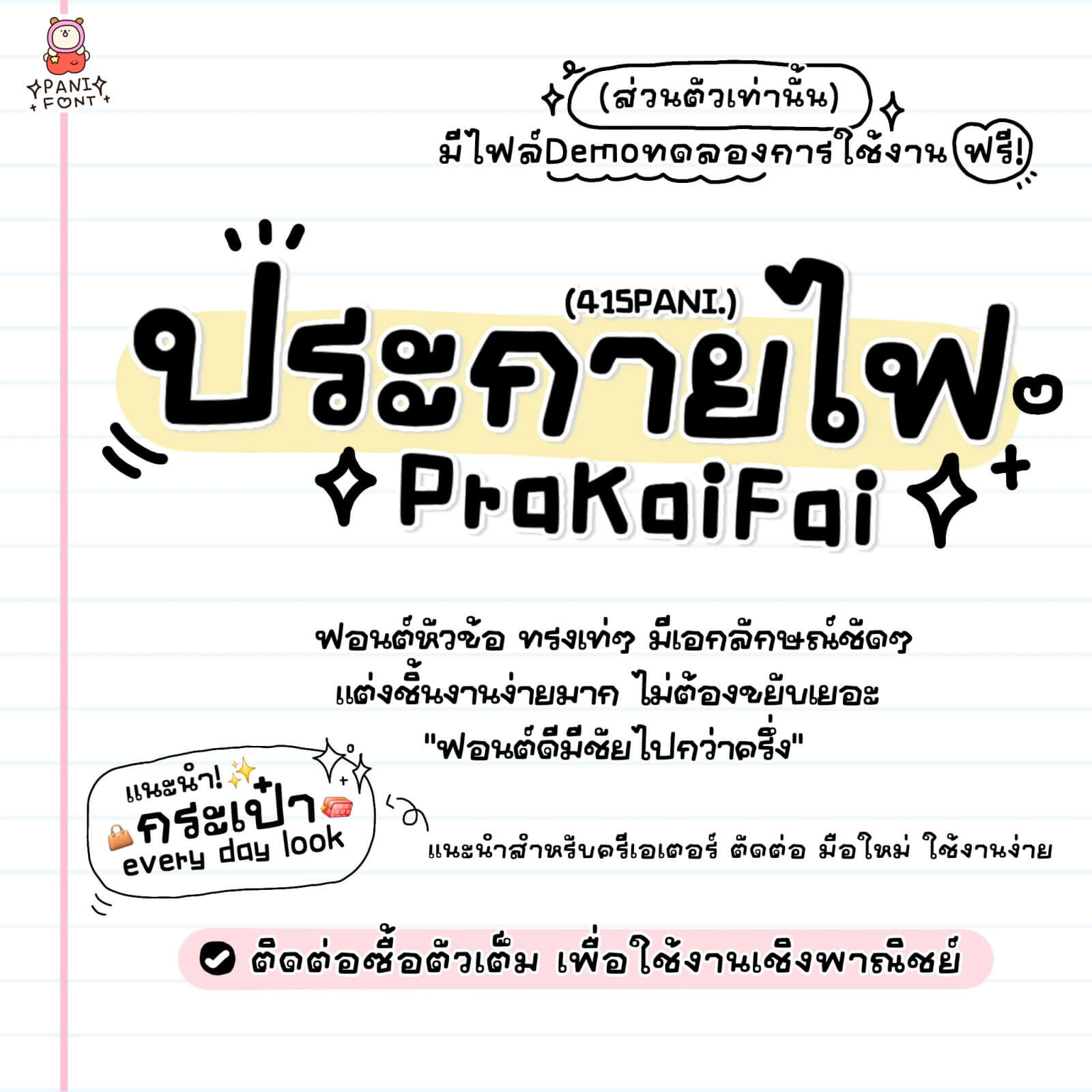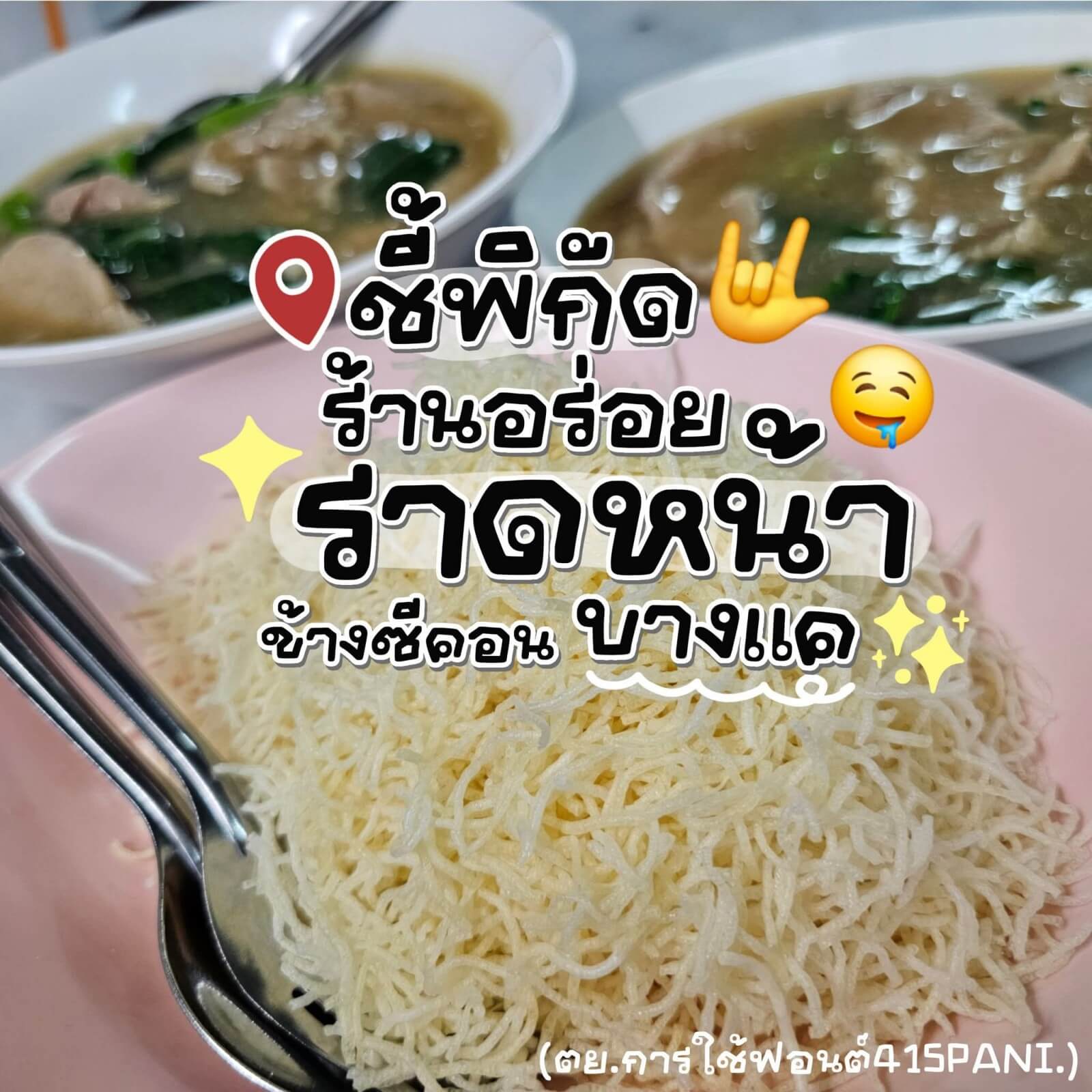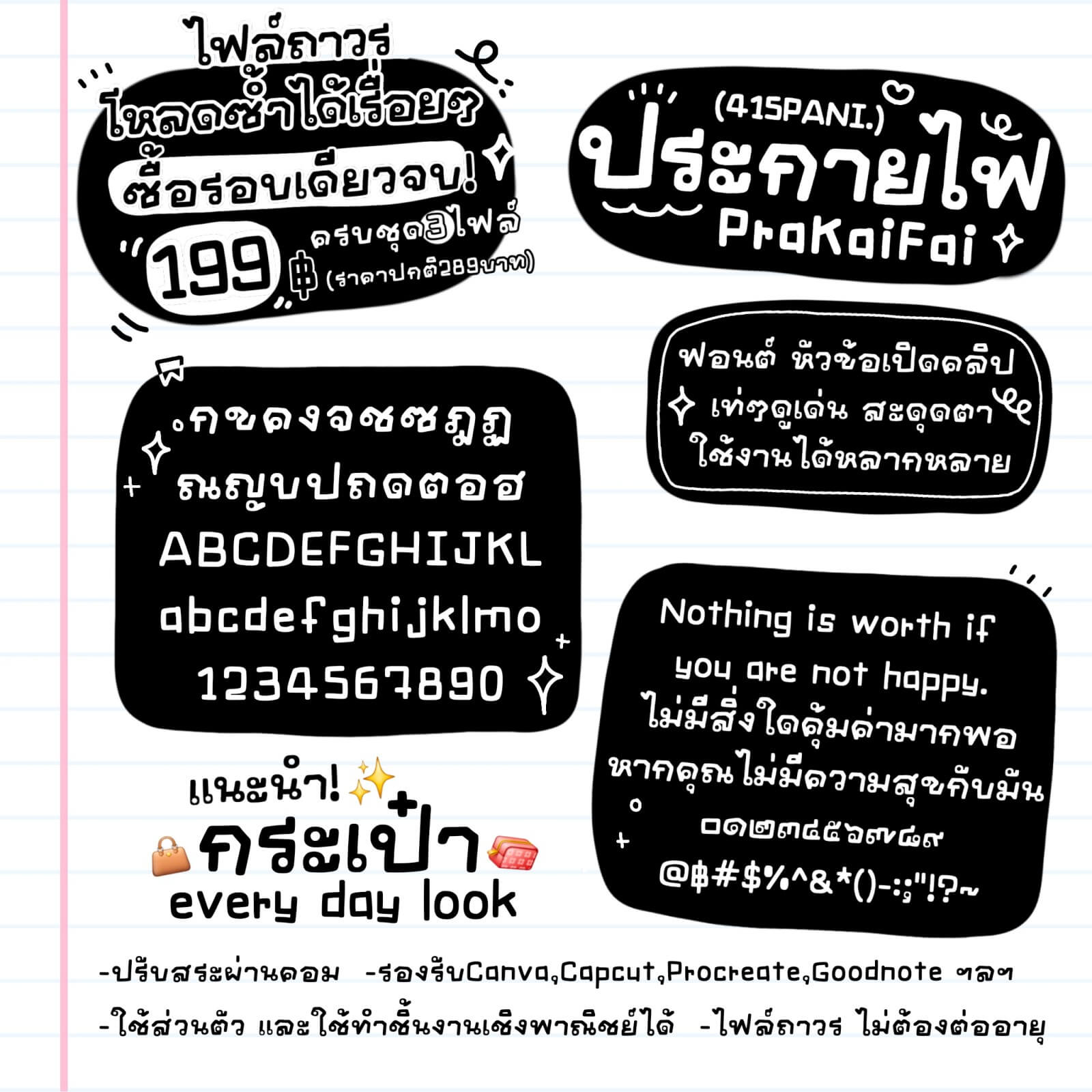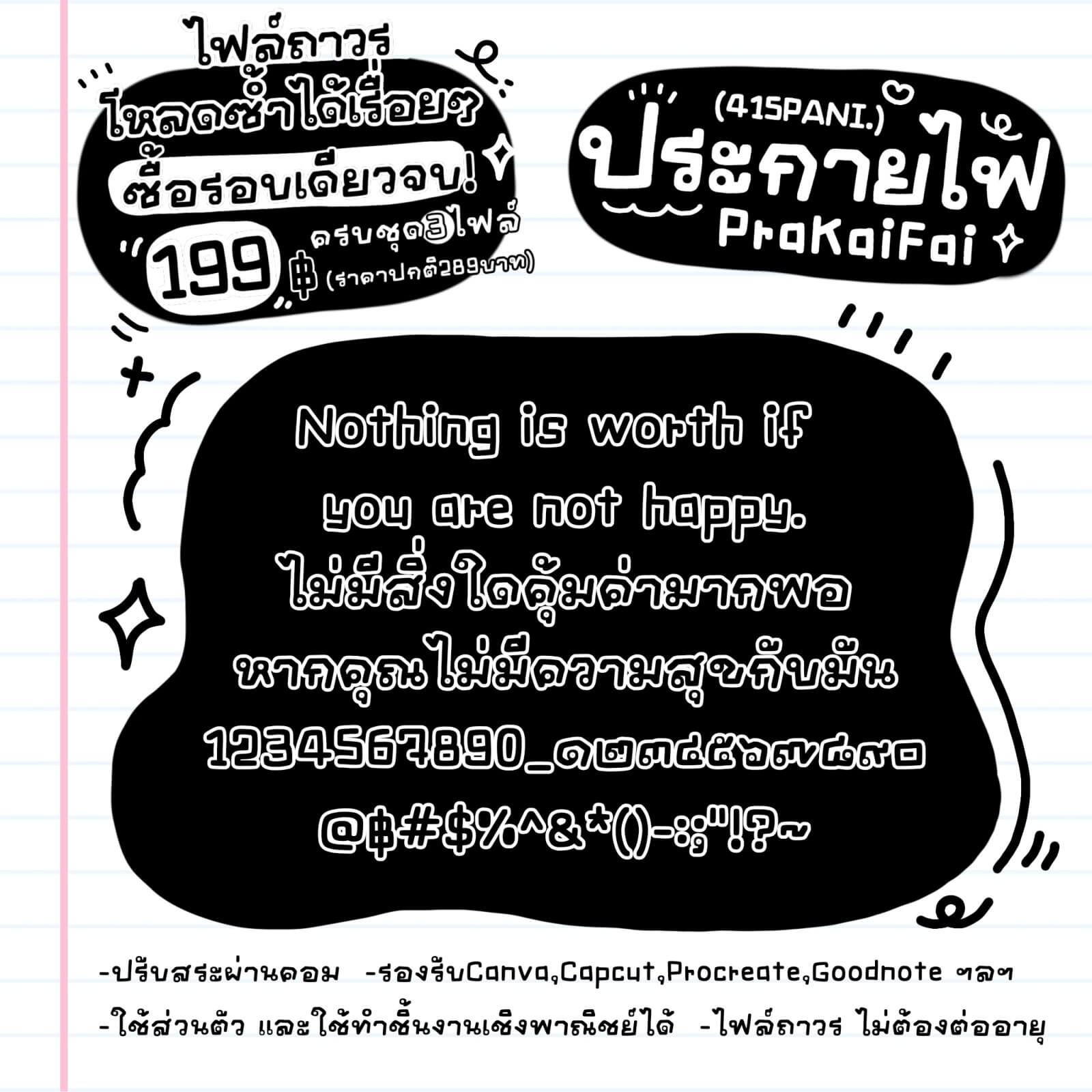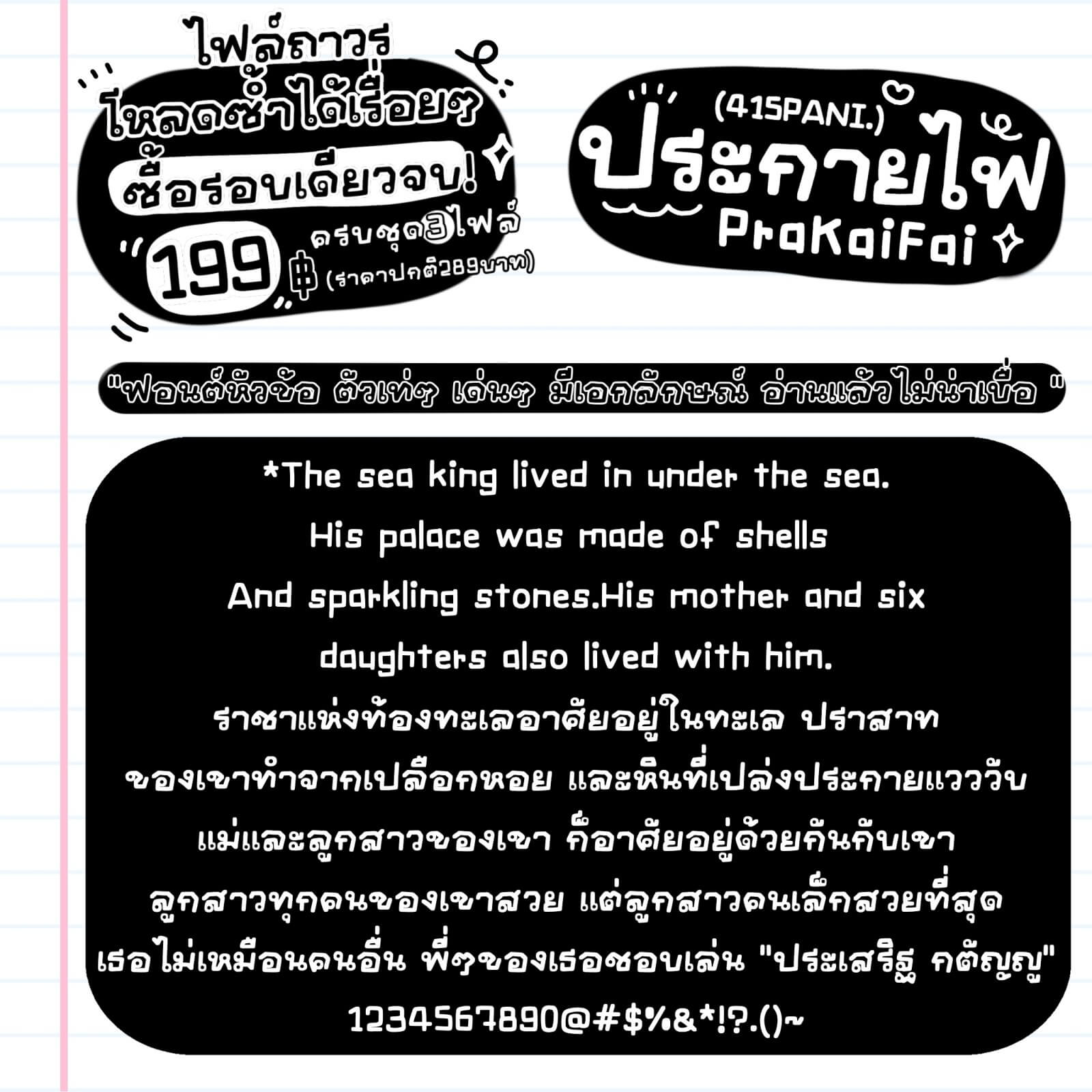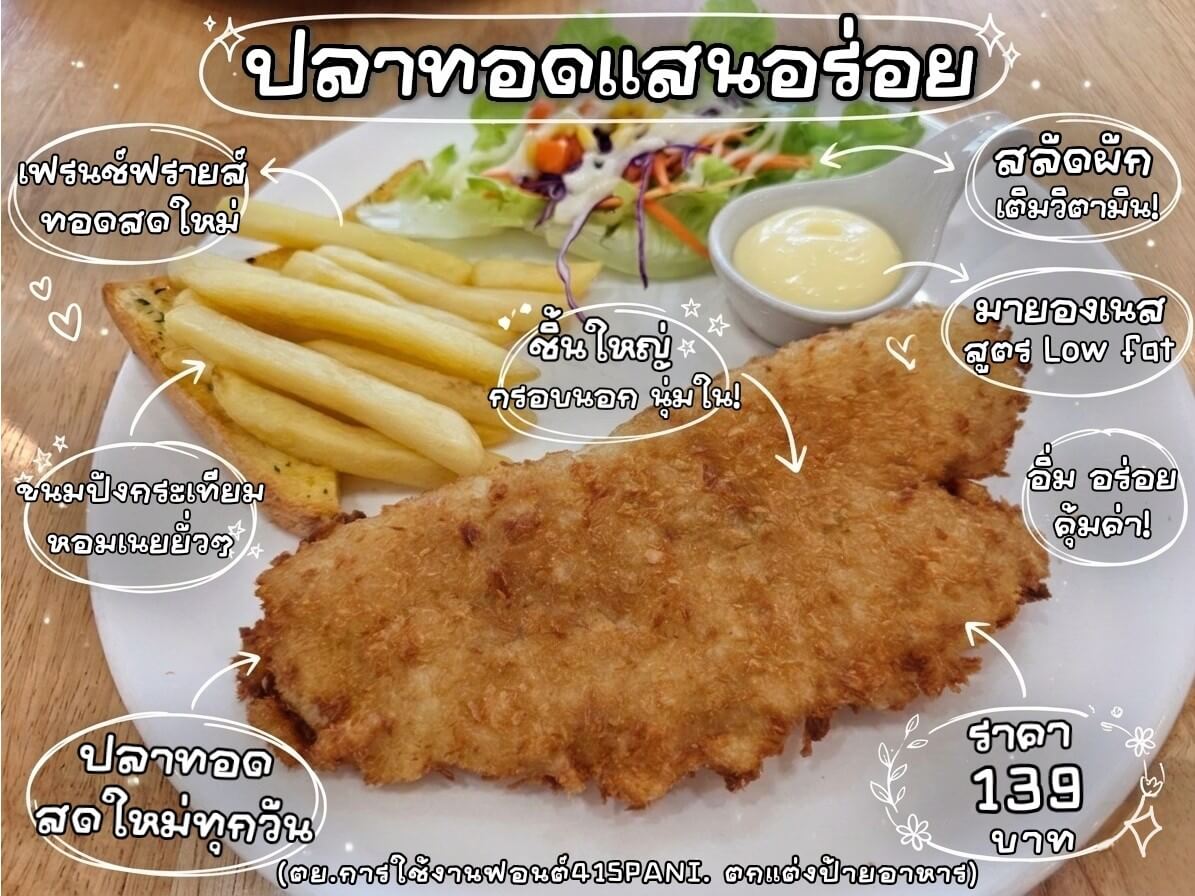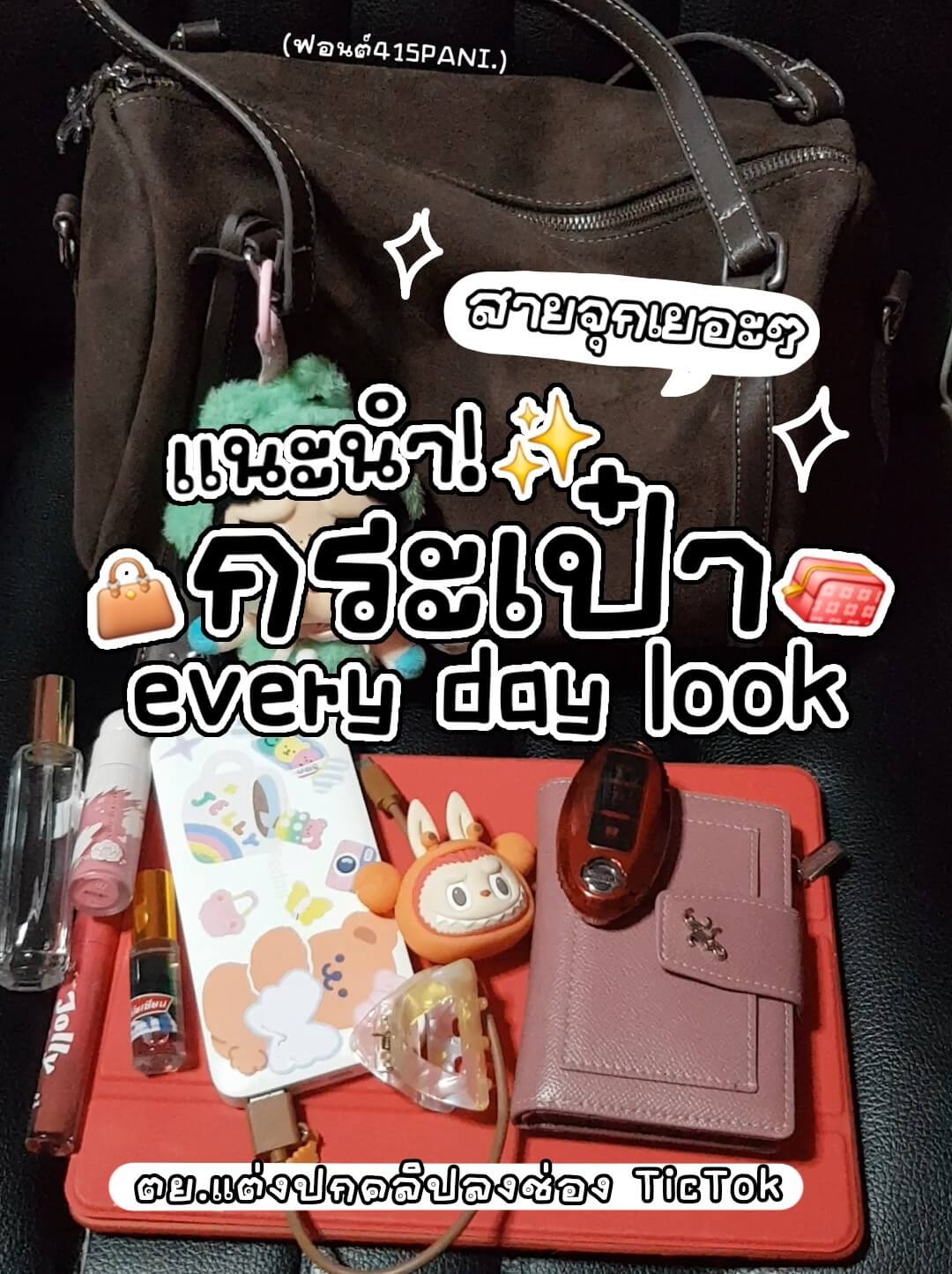
415PANI.ประกายไฟ
ฟอนต์ 415PANI.ประกายไฟ – ฟอนต์หัวข้อ ทรงเท่ๆ มีเอกลักษณ์ชัดๆ ฟอนต์ประกายไฟ แต่งชิ้นงานง่ายมาก แค่พิมพ์ ไม่ต้องขยับเยอะ ก็สวยแล้ว ฟอนต์ดีมีชัยไปกว่าครึ่ง คือเรื่องจริงนะคะ^^